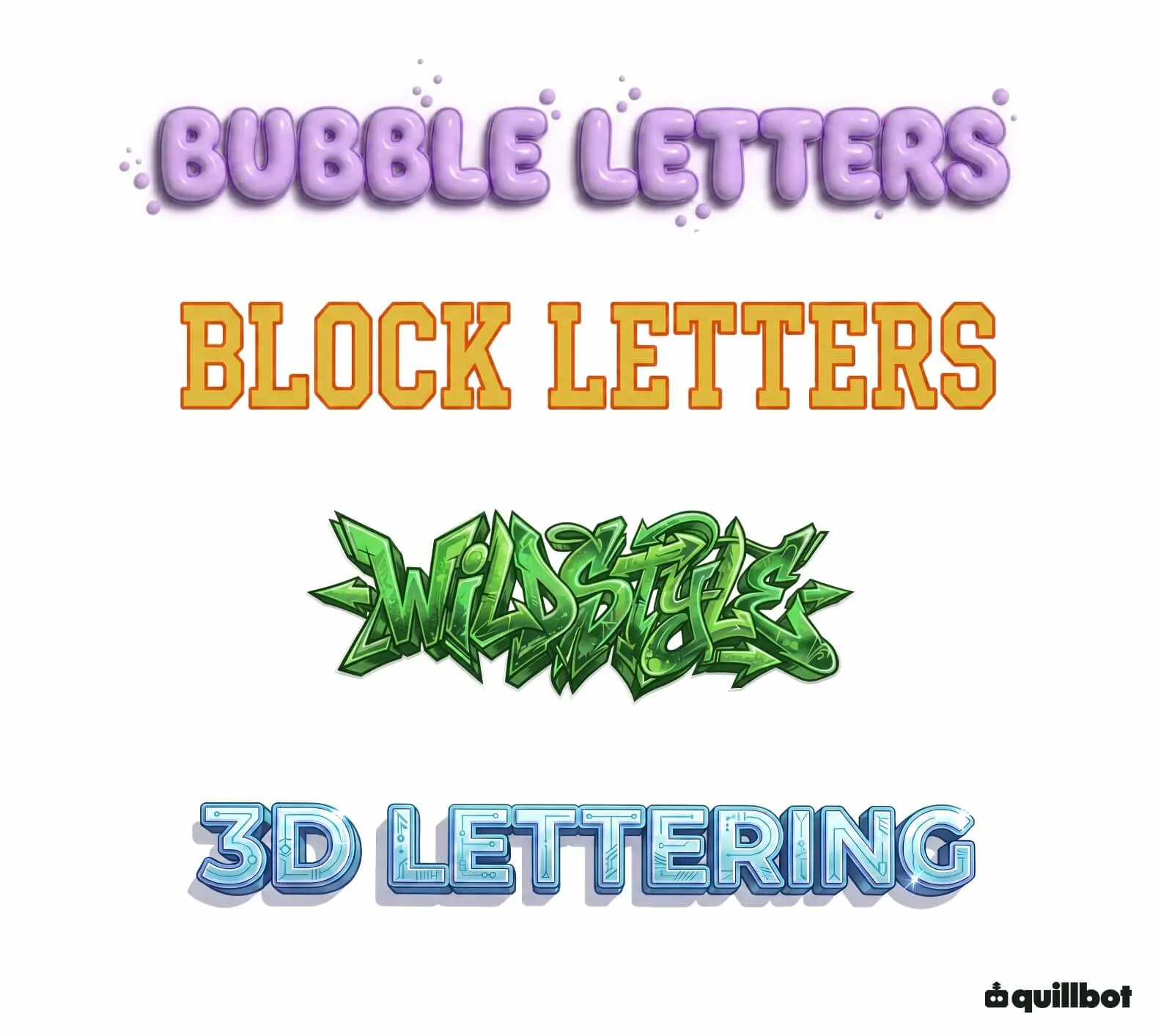
Letras grafite | Estilos e alfabeto de a a z
A escrita em grafite constitui uma forma de arte urbana com estética e caligrafia próprias.
Na arte das letras de grafite, encontramos diferentes estilos, que vão de formas simples e arredondadas até estruturas complexas e entrelaçadas.
Desde as primeiras tags (assinaturas dos artists em forma de pichação), nos vagões do metrô de Nova York na década de 1970, até os designs 3D de hoje, a arte do grafite evoluiu em termos de estilos, técnicas e criatividade.
Com o advento da era digital, as letras de grafite deixaram de se limitar aos trens ou muros urbanos e agora também estão presentes em museus, galerias, roupas e mídias sociais.
As letras de grafite não são tipografia no sentido estrito, mas uma forma de caligrafia e lettering urbano, onde as letras são desenhadas para um espaço específico.
A tipografia utiliza caracteres pré-fabricados — digitais ou de metal/madeira na impressão clássica — idênticos e uniformes, enquanto as letras do grafite são uma arte manual onde cada letra é única.
• As letras de grafite são uma forma de caligrafia e lettering urbano, com estilos próprios que evoluíram das tags dos anos 1970 para composições complexas, coloridas e tridimensionais.
• A arte do grafite reúne diferentes técnicas e estilos, como Tag, Bubble Letters, Wildstyle, Block Letters, 3D e Tag Reto, utilizando tanto tinta spray quanto ferramentas digitais.
• Hoje, as letras de grafite ultrapassam os muros das cidades, influenciando áreas como design gráfico, moda, publicidade, mídias sociais, arte contemporânea e cultura pop.
• Entender a história, as técnicas e os estilos do grafite ajuda a reconhecer sua importância como uma das expressões mais marcantes da comunicação visual urbana.
Letras de grafite: história e evolução
O grafite surgiu na segunda metade do século XX nos Estados Unidos, criado com tinta spray e letras estilizadas.
Naquela época, era visto pelas autoridades e por grande parte da sociedade como um ato de vandalismo.
Na verdade, sendo literal, a prática de fazer grafites teve origem no século I a.C., quando o conceito de “escrever em paredes” já era uma forma de comunicação.
A utilização de paredes como espaço público de expressão é uma prática que remonta ao Império Romano e à Grécia Antiga, onde foram encontradas inscrições que variavam de frases de amor a mensagens como “Eu estive aqui”.
Voltando para os dias atuais, a escrita de grafite, como é conhecida hoje, surgiu no final da década de 1960 na Filadélfia e se popularizou nas ruas e vagões do metrô de Nova York durante a década de 1970.
Artistas de grafite, como Taki 183, popularizaram as tags como uma marca pessoal, o que impulsionou uma rápida evolução das letras do grafite em direção a uma caligrafia maior, mais estilizada e colorida, dando origem à arte urbana e contribuindo com a cultura hip hop.
O grafite não se limita mais à tinta spray em paredes; a era digital transformou as telas na nova “parede”, permitindo que ela alcance todos os tipos de público.
A Geração Z está usando letras de grafite clássicas como ferramenta visual. Estão digitalizando a arte urbana, com caligrafia estilizada e legível para web design, publicidade, moda, arte e mídias sociais.
A escrita em grafite deixou de ser apenas um ato de vandalismo e agora é considerada uma forma de arte contemporânea. Foi de simples assinaturas à mão livre com letras cursivas para desenhos abstratos e letras em 3D.
A palavra graffiti é um termo helenístico que vem do grego γράφειν e significa “escrever”, “gravar” ou “riscar”.
O termo evoluiu em latim até chegar ao italiano graffito (singular) e graffiti (plural), que significa “rabisco” ou “marca”.
Em português, usa-se a forma adaptada “grafite” (ou “grafites” no plural).
Técnicas de letras de grafite
As técnicas para pintar e dar forma às letras de grafite focam no controle do spray e na aplicação de camadas.
Algumas técnicas relacionadas ao controle de aerossóis são:
• Fat cap (traço espesso): é um bico que permite fazer linhas largas, preencher rapidamente grandes superfícies e criar assinaturas grandes.
• Skinny cap (traço fino): é um bico estreito para criar linhas finas e detalhes precisos.
• Controle da distância: a distância entre o jato e a superfície afeta a espessura, a intensidade e a definição do traço.
• Velocidade de pulverização: a velocidade com que o jato se move influencia a quantidade de tinta aplicada e a uniformidade da linha.
Relativamente à aplicação das camadas, os passos a seguir são:
• Esboço: guia inicial feito com linhas claras para emoldurar as letras.
• Preenchimento: aplicação da cor interna, geralmente recomendada na ordem de tons mais claros para mais escuros. Cores escuras, como preto, azul ou marrom, cobrem facilmente as cores mais claras em caso de erro.
• Fundo: cor externa que destaca as letras e ajuda a corrigir imperfeições no preenchimento.
• Contorno: linha final feita com caneta de ponta fina para definir as bordas.
• Detalhes: incorporação de glitter, sombras 3D e contorno externo.
Nas técnicas digitais para criação de letras de grafite, o uso de tinta spray é substituído por ferramentas de software, mesas digitalizadoras e vetores.
O processo é semelhante ao do formato físico, pois são utilizados pincéis digitais que simulam a textura e os efeitos do spray. Mas, com as vantagens da edição digital, como a correção de erros, o uso de camadas e a aplicação de filtros.
Técnicas de letras de grafite: exemplos
Algumas técnicas de coloração baseadas no círculo cromático para criar efeitos em letras de grafite são:
• Efeito de céu: branco ou azul claro (acima), azul turquesa (centro) e azul marinho (abaixo)
• Efeito degradê de fogo: vermelho (em cima), laranja (no centro) e amarelo (em baixo)
• Efeito galáxia: rosa (parte superior), roxo (centro) e violeta ou preto (parte inferior)
• Efeito pôr do sol: amarelo (parte superior), laranja (centro) e cor roxa ou violeta (parte inferior)
• Efeito néon: verde (em cima), verde limão fosforescente (no centro) e verde (em baixo)
• Efeito metálico: azul escuro (parte superior), marrom ou preto (centro) e dourado ou amarelo (parte inferior)
Você pode ler sobre o significado das cores e depois aplicar esse conhecimento para criar a sua tag com letra de grafite digital com o gerador de imagem IA e a ferramenta de desenho do Quillbot.
Estilos de letras de grafite
Os estilos de letras de grafite evoluíram de assinaturas e frases curtas, como frases feministas em muros de rua, para composições artísticas mais complexas.
Nessas assinaturas ou tags, os artistas de grafite geralmente usavam pseudônimos, não nomes próprios.
Alguns dos principais estilos de letras de grafite são:
• Tag: é a base de todo artista de grafite; uma assinatura rápida, com letras em um único traço e uma única cor.
• Bubble Letters: é um estilo mais legível, com letras arredondadas e grossas, fáceis de preencher.
• Wildstyle: letras abstratas com um estilo mais complexo que se entrelaçam.
• Block letters (ou Blockbuster): letras grandes, quadradas e legíveis. Priorizam o impacto visual e a velocidade, pois são projetadas para serem pintadas rapidamente.
• 3D: letras que brincam com a perspectiva para criar profundidade visual.
• Dirty Style: letras que buscam romper com as regras estéticas através de um visual descuidado e desproporcional.
• Characters: as letras são acompanhadas por personagens de histórias em quadrinhos ou desenhos animados.
Letras Grafite
Nota
No Brasil, durante a década de 1980, consolidou-se em São Paulo um estilo de escrita urbana conhecido como tag reto.
Inspiradas nas inscrições presentes em capas de discos de heavy metal e em logotipos de bandas de rock, essas letras passaram a ser desenhadas com traços retos, estreitos e verticais, formando uma identidade visual única.
Diferentemente de outros estilos de grafite, o tag reto prioriza a assinatura do autor, utilizando letras alongadas e angulosas que ocupam fachadas e edifícios altos.
Com o passar dos anos, esse estilo tornou-se um dos principais símbolos da escrita urbana brasileira e hoje é reconhecido internacionalmente por sua estética singular, influenciando artistas, designers e pesquisadores da arte urbana.
Influência das letras de grafite
A estética das letras de grafites adquiriu grande importância na cultura visual contemporânea.
Algumas das áreas em que a influência das letras de grafite se reflete são:
• Moda: muitas marcas construíram sua identidade visual com base em letras de grafite. Inclusive marcas de luxo, como Gucci e Louis Vuitton, colaboraram com artistas urbanos para estampar seus designs e assinaturas em roupas, bolsas e sapatos.
• Design gráfico e identidade visual: o grafite transformou a tipografia ao introduzir formas abstratas e expressivas. Na identidade visual de marcas, essa tipografia atua como uma conexão cultural com o público mais jovem, rompendo com a neutralidade e a legibilidade de fontes tradicionais como Arial ou Helvetica.
• Mídias sociais: a digitalização das letras do grafite permitiu que usuários de plataformas como Instagram e TikTok aplicassem tags ou grafites — como adesivos — às suas postagens e stories. Além disso, essas redes se tornaram uma tela global para artistas de grafite, dando visibilidade ao seu trabalho e alcançando um público mais amplo.
• Arte: a caligrafia urbana revolucionou a arte contemporânea ao levar a arte de rua para espaços como galerias de arte e museus.
• Cultura pop: essas letras tiveram uma influência significativa na música, especialmente no hip hop, tornando-se um elemento visual recorrente em capas de álbuns e videoclipes. Essa estética também influenciou o cinema.
Perguntas frequentes sobre letras grafite
Letras de grafite são em 3D?
O efeito grafite 3D — um estilo de letra com sentido de profundidade, sombras e contrastesé apenas um dos estilos possíveis dentro do grafite.
Existem diversos estilos de letras, por exemplo:
• Tag: assinatura do artista simples e rápida, sem efeito 3D.
• Bubble Letters: letras arredondadas e volumosas, geralmente bidimensionais.
• Block Letters (Blockbuster): letras grandes e retas, que podem ou não ter profundidade.
• Wildstyle: letras complexas e entrelaçadas, normalmente sem foco no efeito 3D.
• 3D: estilo que utiliza perspectiva, sombras e profundidade para dar a impressão de que as letras saltam da superfície.
Se você quiser criar uma letra grafite de A a Z, pode usar tanto o gerador de imagem IA do Quillbot quanto a ferramenta de desenho!
Qual a diferença entre estilo de letras e tipos de letras?
Tipos de letras dizem respeito à forma básica ou à estrutura visual das letras. Por exemplo, em relação às letras estilo grafite, podem ser um tipo de:
• Letras redondas
• Letras quadradas
• Letras abstratas
• Letras finas ou grossas
estilos de letras são maneiras reconhecidas de criar e organizar essas formas dentro de um tema. Por exemplo, o estilo de letra grafite pode ter influência de outros estilos, como:
• Tag
• Bubble Letters
• Wildstyle
• Block Letters
• 3D
• Dirty Style
• Characters
Se você quiser criar uma letra grafite de A a Z, você pode usar tanto o gerador de imagem IA do Quillbot quanto a ferramenta de desenho!
Qual a diferença entre estilos de letras e tipos de fontes?
Tipos de fontes e tipos de letras são praticamente sinônimos. A primeira se refere à forma mais geral de criar uma letra, enquanto a segunda é mais específica.
Assim como os tipos de letras, os tipos de fonte definem características da fonte, suas formas e curvaturas. Tipos de fontes conhecidas são as famílias tipográficas:
Já o estilo de letra trata de um conjunto de características pré-definidas que criam letras reconhecidas pelas pessoas, como:
Se você quiser criar uma letra grafite de A a Z, você pode usar tanto o gerador de imagem IA do Quillbot quanto a ferramenta de desenho!
Qual é a diferença entre tipos de letras e tipos de fontes?
Tipos de letras e tipos de fontes significam praticamente a mesma coisa, sendo utilizados como sinônimos.
Tipos de letras se referem mais às características gerais dos alfabetos.
Tipos de fontes consideram mais as características específicas de cada fonte.
Se você quiser entender mais sobre conceitos, como tipos de letras e tipos de fontes, consulte o Chat IA gratuito do Quillbot.
Qual é o significado de tipografia?
Tipografia é uma palavra que vem do latim renascentista, typographia. Typos (τύπος) vem da língua grega e significa “impressão” e -graphia (-γραφία), também do grego, quer dizer “escrita”.
Literalmente, o significado original da palavra tipografia era “impressão de escrita”, contrastando com o manuscrito.
Atualmente, tipografia refere-se à arte ou técnica de organizar textos e letras de maneira clara e agradável.